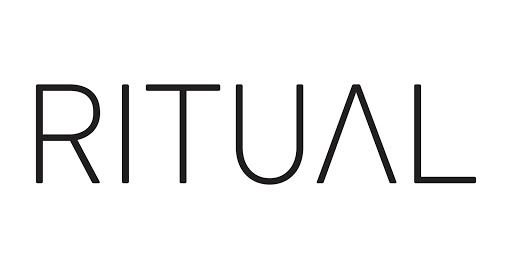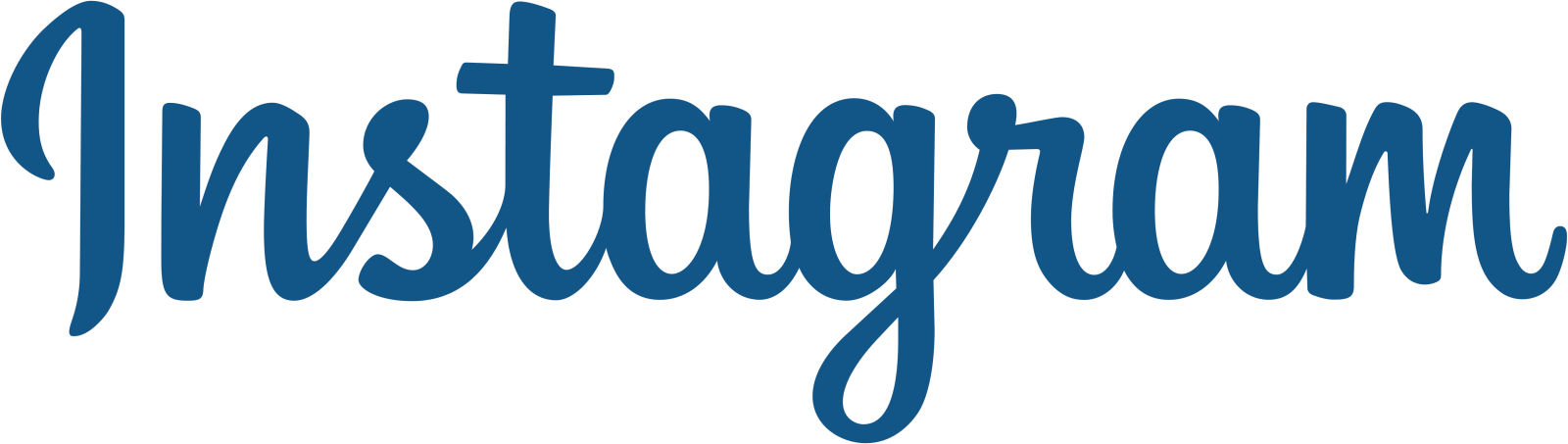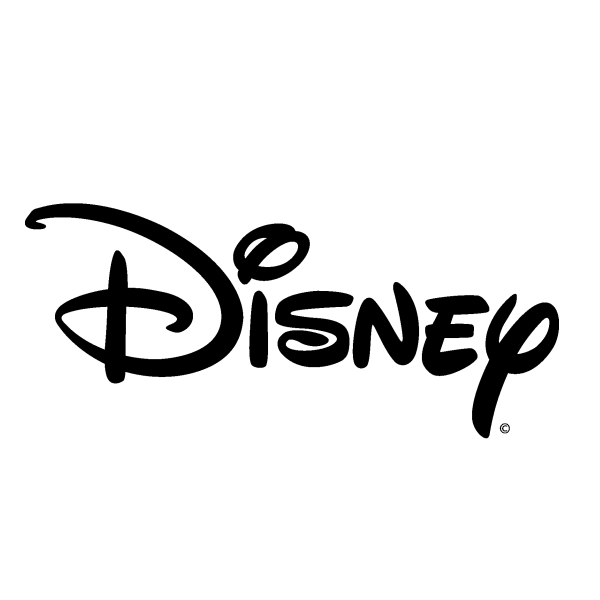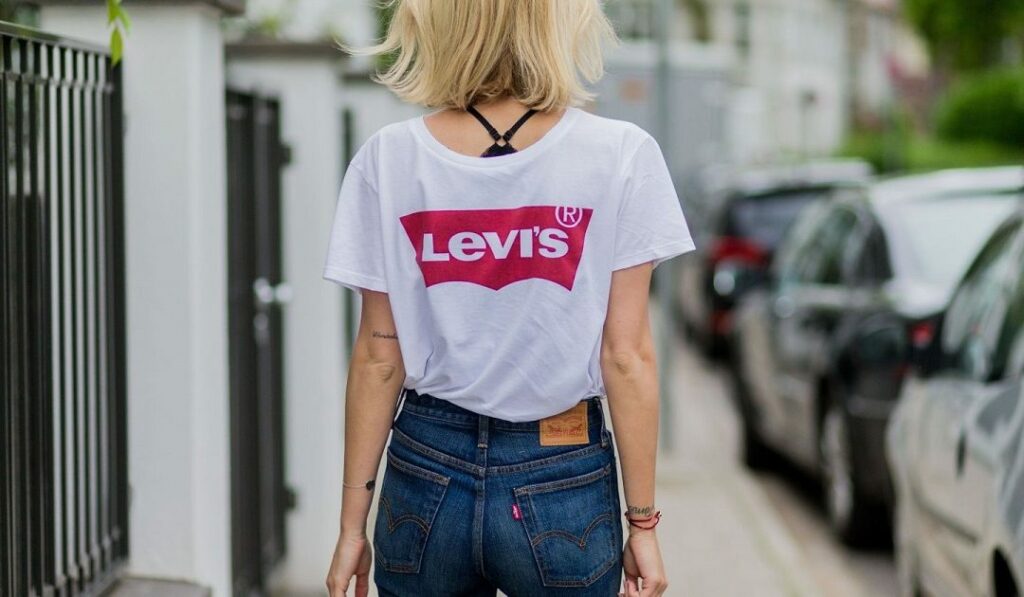
5 font chữ thiết kế logo cơ bản và cách ứng dụng
Để thiết kế một logo hoàn hảo, đòi hỏi rất nhiều thời gian và công sức, trong đó, việc chọn lựa font chữ rất dễ khiến nhiều nhà thiết kế đau đầu. Làm sao để chọn lựa được font chữ phù hợp, lột tả được tính chất, cảm xúc, cũng như những thông điệp mà doanh nghiệp muốn truyền tải đến khách hàng của mình? Hãy tham khảo ngay 5 font chữ thiết kế logo cơ bản dưới đây để ứng dụng vào logo của bạn nhé!
5 font chữ thiết kế logo cơ bản
Dù biết rằng: font chữ là một yếu tố quan trọng của thiết kế logo, nhưng thật khó để lựa chọn! Bằng cách thay đổi font chữ, bạn hoàn toàn có thể thay đổi tâm trạng và thông điệp của thiết kế của bạn. Cho dù đó là cổ điển, tương lai hay hiện đại, font chữ của bạn nên được xem xét cẩn thận và truyền tải thông điệp bạn muốn.
Mẹo: Đừng đánh giá thấp sức mạnh của việc chọn thiết kế font chữ phù hợp và tác động tâm lý sâu sắc của nó đối với khách truy cập của bạn. Các nhà thiết kế có kinh nghiệm hiểu điều này và chọn font chữ của họ rất cẩn thận và có chủ ý. Chúng tôi thường dành hàng giờ để chọn một font chữ cho một thiết kế. - Brad Shaw, Chủ tịch & Giám đốc điều hành, Thiết kế trang web Dallas.
Các kiểu font chữ khác nhau truyền đạt các thông điệp tiềm thức khác nhau đến mọi người, điều này có thể giúp bạn xây dựng nhận diện thương hiệu.
Có một vài loại cốt lõi của kiểu font chữ bạn nên biết trước khi chọn kiểu: Serif, Sans Serif, Hiện đại, Viết tay và Hiển thị. Chúng tôi sẽ xem xét tất cả chúng để bạn có cơ hội tìm hiểu những gì mỗi phong cách truyền tải và cách sử dụng chúng!
#1. Font chữ Serif
Một font chữ serif cổ điển vượt thời gian được liên kết với truyền thống và quyền sở hữu. Các font chữ như Times New Roman thường kích thích một phản ứng tích cực cho các thế hệ cũ, nhưng các doanh nghiệp nhắm đến một đám đông trẻ hơn có lẽ nên chọn một phong cách khác cho logo của họ. Một font chữ serif là một font chữ thiết kế logo tốt cho một thương hiệu muốn liên kết với thời gian và di sản.
The Financial Time là một ví dụ hoàn hảo về font chữ serif cổ điển. Là một tờ báo kinh doanh, logo của nó gợi lên sự tin tưởng, tự tin và uy tín. Logo mang ý nghĩa truyền thống, có ý nghĩa khi đưa ra vấn đề đầu tiên của tờ báo này xuất hiện vào năm 1888!
font-chu-thiet-ke-logo-bee-art-01Logo của Financial Times sử dụng font chữ Serif
#2. Font chữ Sans-serif
Font chữ Sans-serif đã trở lại vào năm 2017, với nhiều thương hiệu nổi tiếng, bao gồm cả Calvin Klein, đã chọn cách nhìn đơn giản, sạch sẽ này cho font chữ logo của họ. Dễ đọc và trung tính theo thiết kế, font chữ này sẽ kết hợp tốt với hầu hết các hình dạng và thiết kế có thể được bao gồm trong thương hiệu của bạn. Chọn loại font chữ này cho một cái nhìn tương lai, hiện đại và đơn giản.
Mặc dù trước đây xuất hiện nhiều hơn với phong cách font chữ hiện đại, sans-serif hiện nay phổ biến hơn serif vì tính dễ đọc và phong cách đơn giản của chúng. Ngày nay, bạn không thể sai với font chữ sans-serif!
Logo của Calvin Klein sử dụng font chữ sans-serif
#3. Font chữ hiện đại
Nếu sự sang trọng và độc quyền là mục tiêu hàng đầu của thương hiệu của bạn, thì việc khám phá các font chữ hiện đại có thể là hướng đi cho bạn. Những kiểu chữ này thường tạo ra một cảm giác tinh tế và phức tạp. Font chữ thiết kế logo hiện đại truyền tải một cảm giác tổng thể về sức mạnh hiệu quả nhất với nhân khẩu học trẻ.
Người ta thường thấy các font chữ hiện đại được sử dụng bởi các doanh nghiệp thu hút nhân khẩu học trẻ hơn. Các công ty khởi nghiệp và các công ty ứng dụng di động khác nhau sẽ đi theo con đường này, giống như ví dụ dưới đây. Ritual là một ứng dụng cho phép bạn đặt thức ăn trước thời hạn và dễ dàng lấy nó, tất cả trong khi tích lũy điểm và phần thưởng để sử dụng khi mua hàng của bạn. Logo của họ thông minh, tinh tế và hiện đại, giống như kinh doanh của họ.
font-chu-thiet-ke-logo-bee-art-03Logo của Ritual sử dụng font chữ hiện đại
Mẹo: Logo cho vay nhiều hơn một chút so với giao diện độc đáo. Nếu thiết kế logo của mọi công ty được thể hiện ở Helvetica, điều gì sẽ khiến nó trở nên độc đáo? Chắc chắn tôi đã sử dụng rất nhiều tác phẩm kinh điển trong logo, nhưng đó là nơi tôi để dự án và chủ đề nói với tôi. - Chad Birenbaum, Đồng sáng lập & thiết kế, Thiết kế Duckpin
#04. Font chữ viết tay
Trang trọng, thanh lịch và nữ tính. Một thương hiệu muốn hiển thị các loại đặc điểm này nên sử dụng font chữ khó hiểu, nhưng hết sức thận trọng. Logo thường được thay đổi kích thước và điều này có thể gây ra sự cố khó đọc với logo kiểu chữ viết tay. Văn bản có font chữ theo kịch bản nên ngắn, vì văn bản chữ thảo mở rộng có thể làm căng mắt người đọc.
Như đã đề cập ở trên, cần có một loại nhãn hiệu nhất định để tạo ra một font chữ viết tay hoặc chữ thảo. Những loại font chữ này rất vui nhộn, nhưng có thể nhanh chóng biến giống như trẻ em. Đảm bảo rằng nếu bạn đang sử dụng font chữ viết tay cho logo của mình, nó phù hợp với thông điệp bạn đang cố gắng truyền tải tới đối tượng mục tiêu của mình.